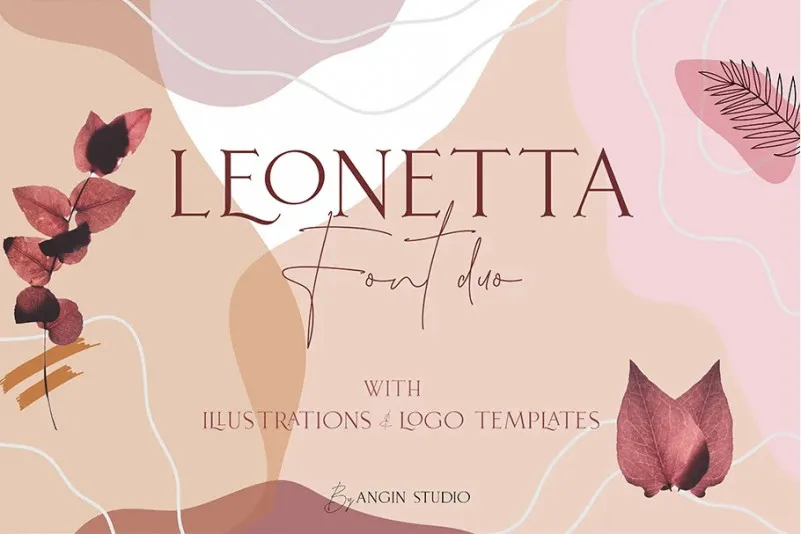
Leonetta Font Duo
Agora, apresentamos para você a Leonetta Font Duo – uma combinação inovadora que traz texto com textura rica e alternativas estilizadas. Desenvolvida pela Angin Studio no site de criação 99designs, a fonte imita uma escrita natural, oferecendo ligaturas e alternativas de caracteres para um visual mais elegante e autêntico. Leonetta Script foi projetada especialmente para mimetizar o estilo da escrita à mão real. Oferece múltiplas opções de ligação e alternativa de caracteres que ajudam a criar uma aparência natural na escrita, tornando seu uso ainda mais envolvente e sofisticado. Por sua vez, Leonetta Serif é igualmente diversificada e vibrante com seus belos detalhes. Possui um conjunto amplo de ligaturas e alternativas de caracteres que permitem a você misturar e combinar as letras de maneiras lúdicas, proporcionando uma expressão visual única que reflete o jeito como você pensa ou fala. Com Leonetta Font Duo em sua coleção, você terá a flexibilidade para criar um layout que transmita uma mensagem visual que seja autêntica e emocionalmente conectada. Adapte suas criações da maneira que quiser, desde um texto com personalidade até uma página inteiramente decorada. Completando essa dupla de fontes serif, a Leonetta Font Duo é perfeita para aqueles que procuram texturas ricas e alternativas sofisticadas em cada letra.